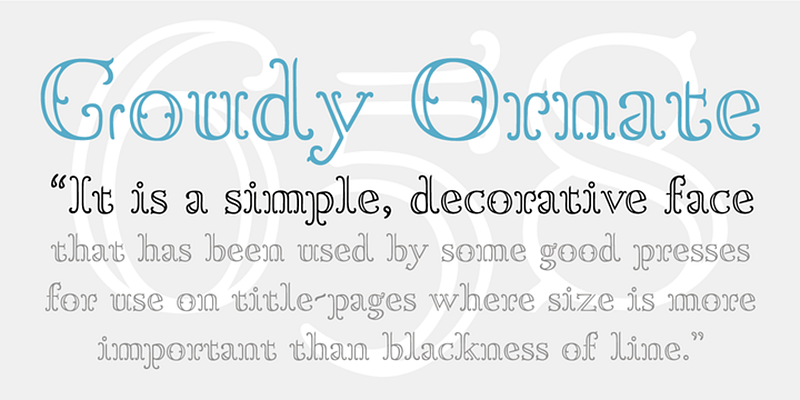
Die LTC Goudy Ornate wurde 1931 von Frederic W. Goudy entworfen. Diese neue digitale Version von Lanston enthält einen Kleinbuchstaben und einen vollständigen Zeichensatz im Stil von Frederic W. Goudy.